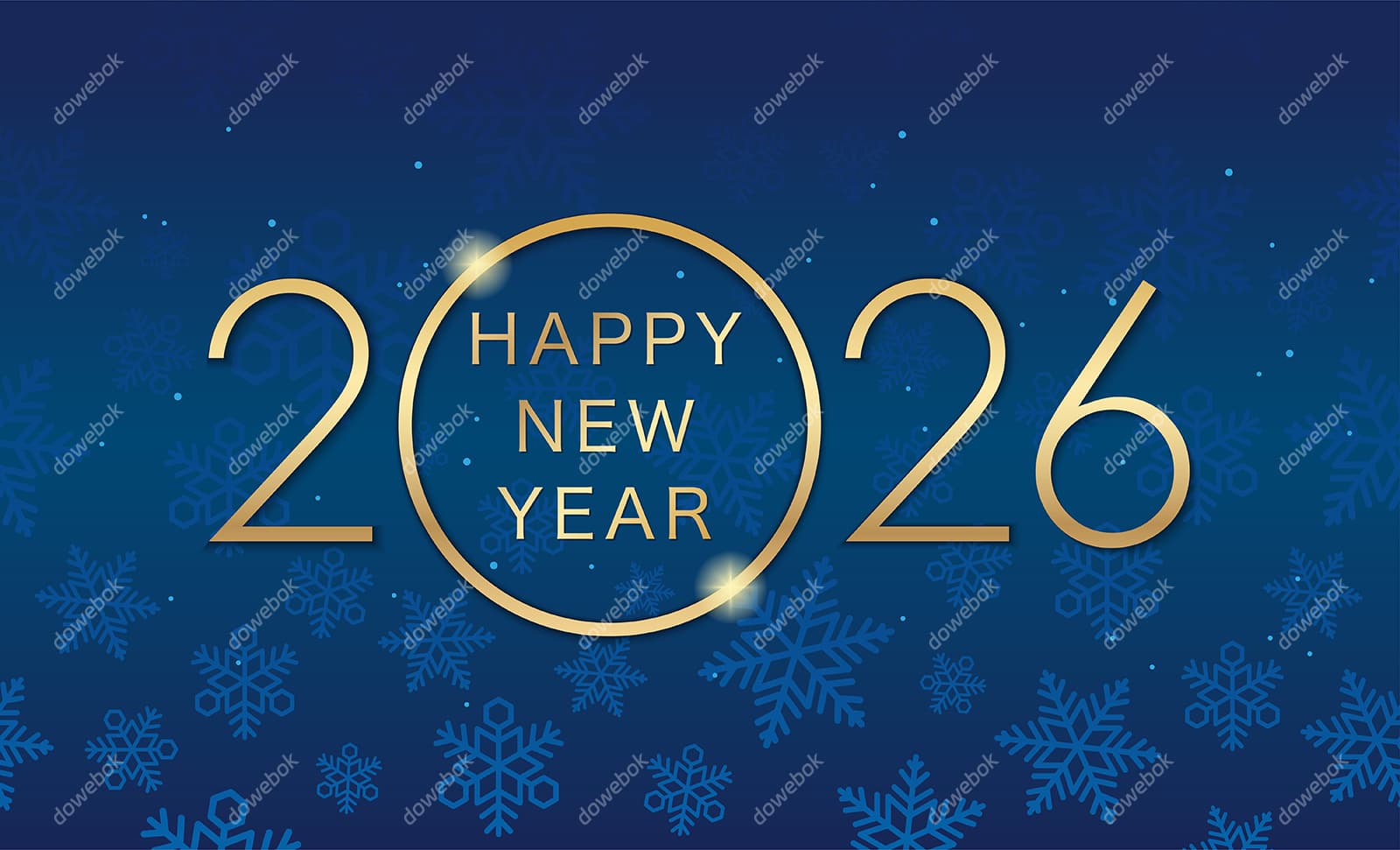
这是一款金色数字和雪花设计的 2026 新年快乐矢量素材,渐变藏蓝背景铺着浅蓝雪花暗纹,烘托冬日氛围。鎏金 “2026” 字体对称分布,中间金环内嵌 “Happy New Year” 字样,星光点缀更添精致感。整体以蓝金配色融合冬日元素与简约版式,既显跨年的雅致格调,又用雪花细节强化季节氛围,清冷中透出温馨的节日质感。